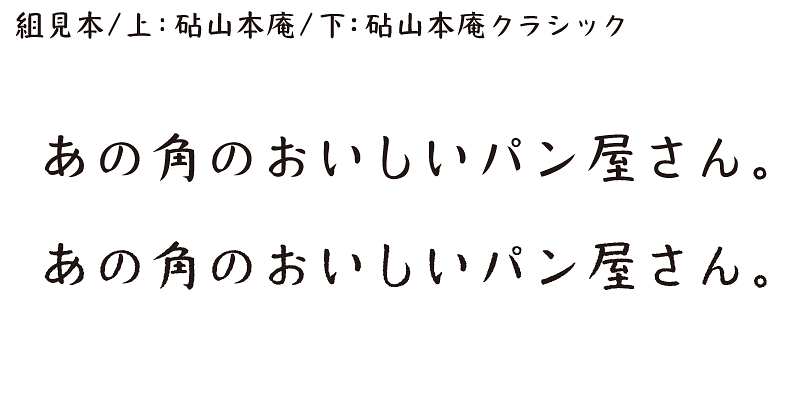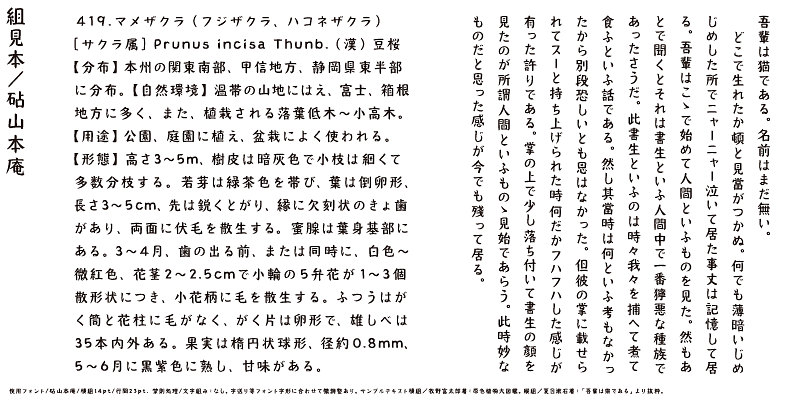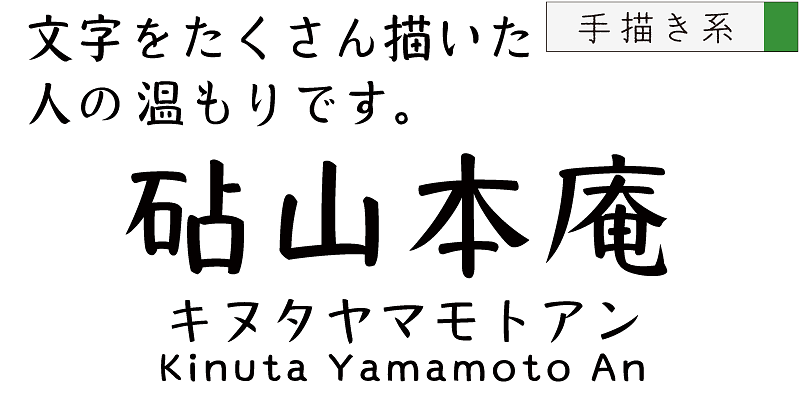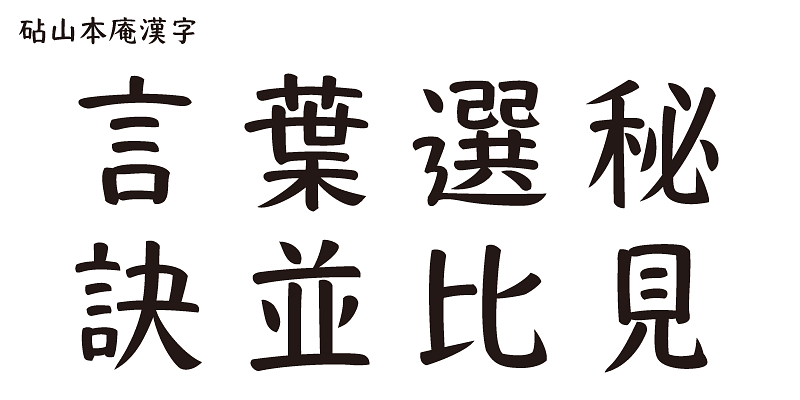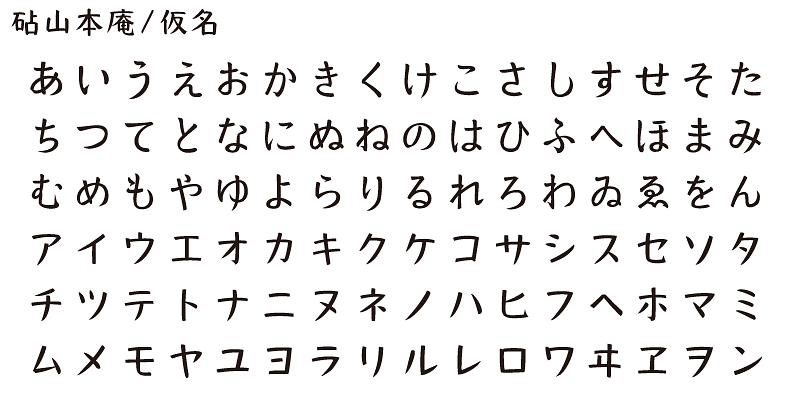
Michiya Yamamoto의 손글씨를 바탕으로 한 Yamamotoan은 노련한 서예가 특유의 풍부한 서예 정수를 지니고 있습니다. 편지 형태에서 일종의 심오함을 느낄 수 있습니다. 시간이 흐를수록 Yamamotoan 디자인의 중요성은 더욱 널리 인식될 것입니다. 긴 텍스트에서도 청량감이 느껴집니다.
일본어의 특징 중 하나는 가나 음절 문자가 있다는 것입니다. 가나 문자는 일본어로 소리를 표현하고 중국에서 가져온 텍스트를 일본어로 번역하기 위해 일본에서 발명되었습니다. 한자/중국어 표의 문자에서 일본어 단어와 표현을 만들려면 가나 문자가 필요합니다. 모호한 부분이 있을 수 있지만, 이 단어와 표현에는 좁고 인구 밀도가 높은 일본 땅에 사는 사람들의 삶의 따뜻함과 온유함이 담겨 있습니다.
Kinuta Font Factory는 가나 문자가 일본어 문자의 근원이라고 믿으며, 가나 문자를 개선하면 일본어 텍스트가 더욱 매력적으로 발전할 것이라고 생각합니다. 평균적으로 일본어 텍스트의 60%는 가나 문자로 구성됩니다. 이들 문자의 모양을 바꾸면 텍스트의 시각적 모양이 변경됩니다. 단순하고 역동적이며 곡선적인 가나 문자를 사용한 타이포그래피 표현의 가능성은 무궁무진하며 일본어 텍스트의 풍부함은 가나 문자에 달려 있습니다. 이것이 Kinuta Font Factory가 다양한 가나 서체 변형을 제공하는 이유입니다.